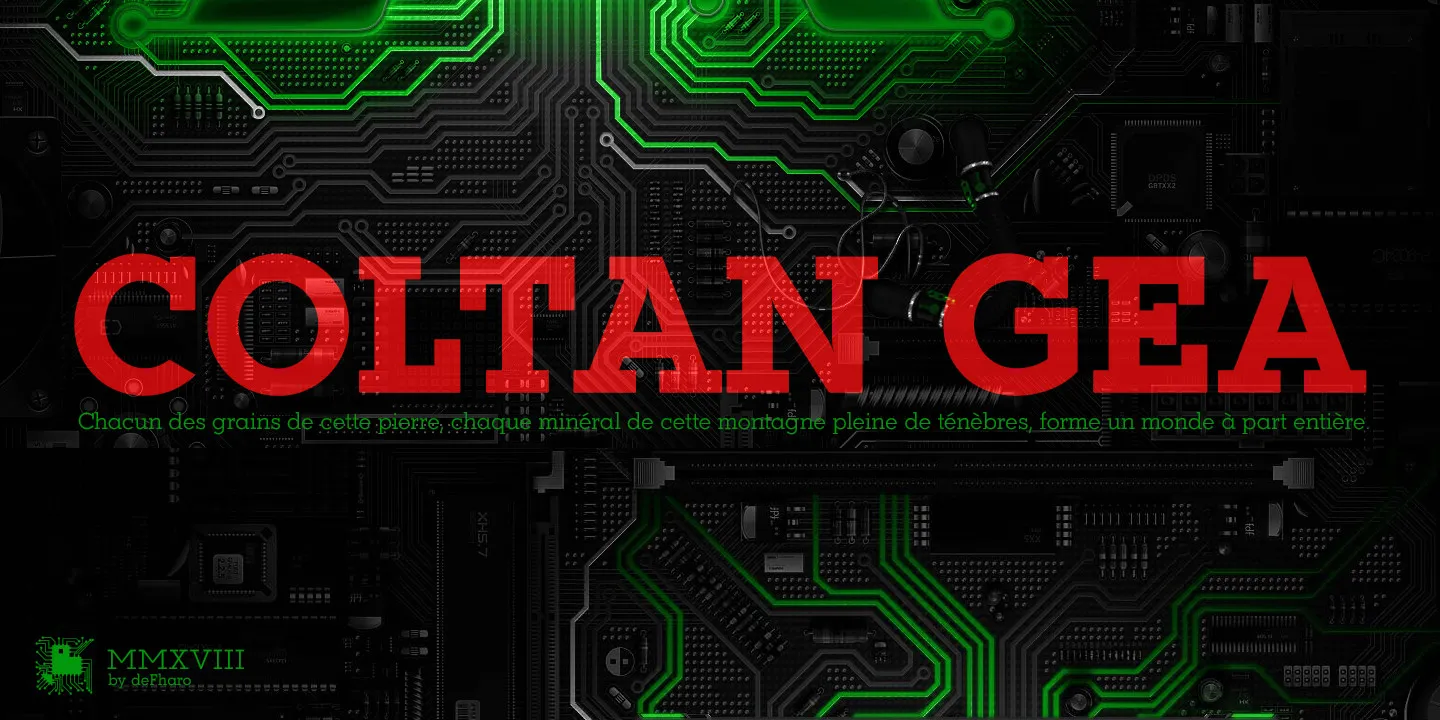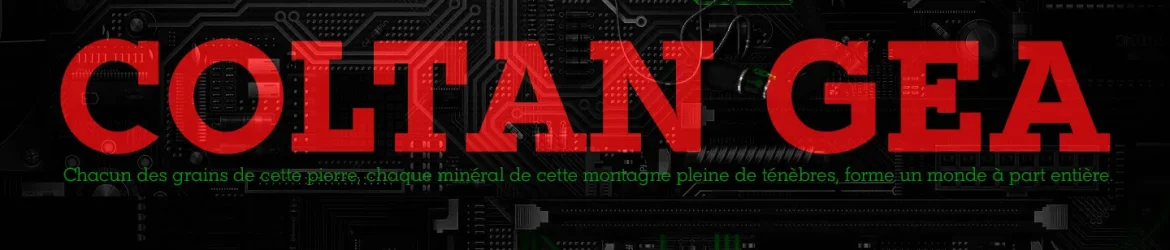
A Coltan Gea é uma família tipográfica Slab Serif composta por seis pesos, incluindo versões itálicas, todas elas contendo letras pequenas e símbolos de criptomoedas. Esta fonte geométrica e minimalista tem modulações neo-grotteanas e ângulos levemente arredondados. O tipo apresenta alternativas para letras e números, além de capas menores e funções avançadas do OpenType que garantem uma leitura perfeita em qualquer tamanho. Os parâmetros métricos, proporções e kerning foram cuidadosamente configurados pelo designer defharo para criar um layout visual atraente e confortável para o leitor. A Coltan Gea é perfeita tanto para aplicativos digitais quanto impressos, com seu uso em variadas aplicações como headlines ou parágrafos de texto. Para quem busca uma fonte moderna e funcional, esta família de tipo é um ótimo investimento.